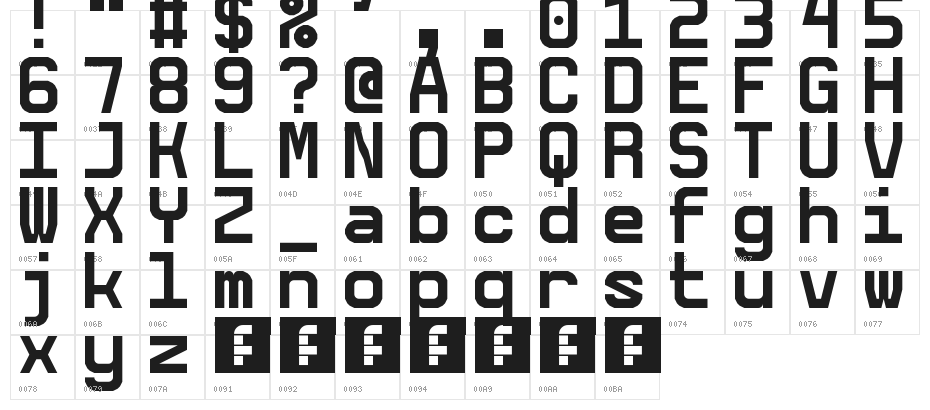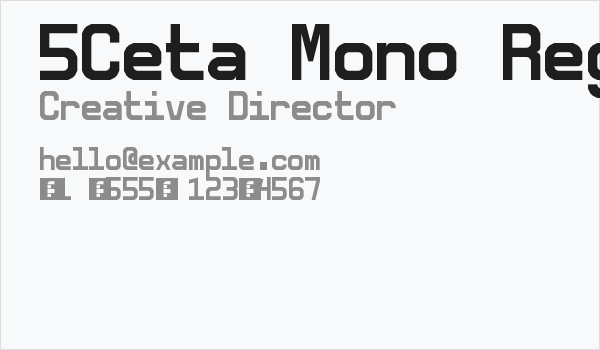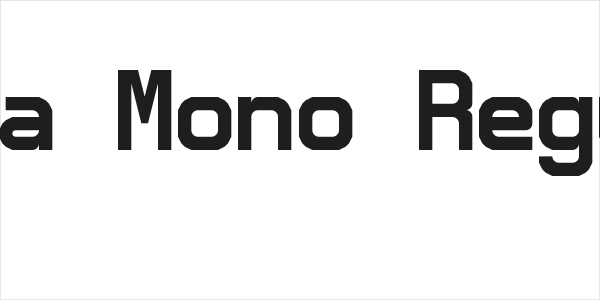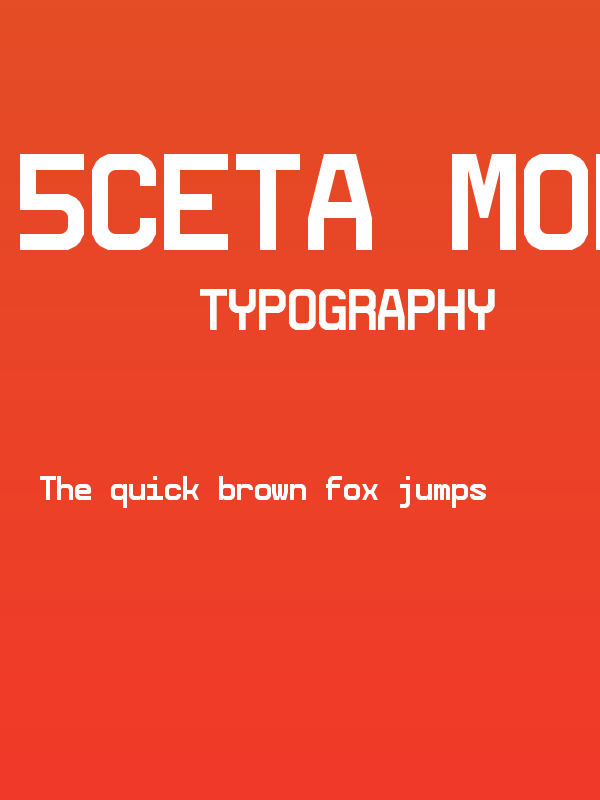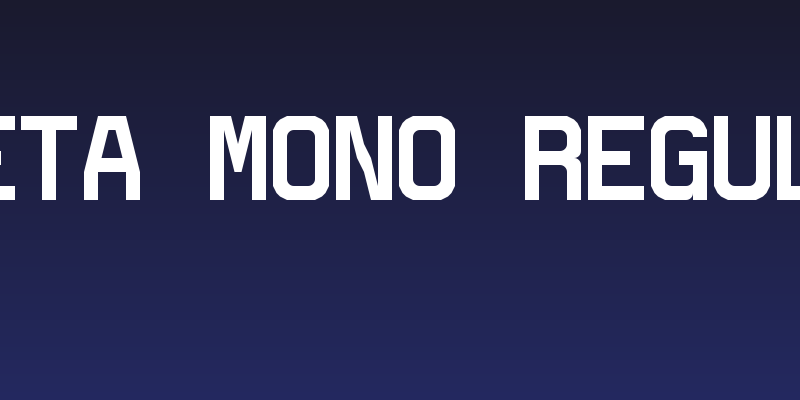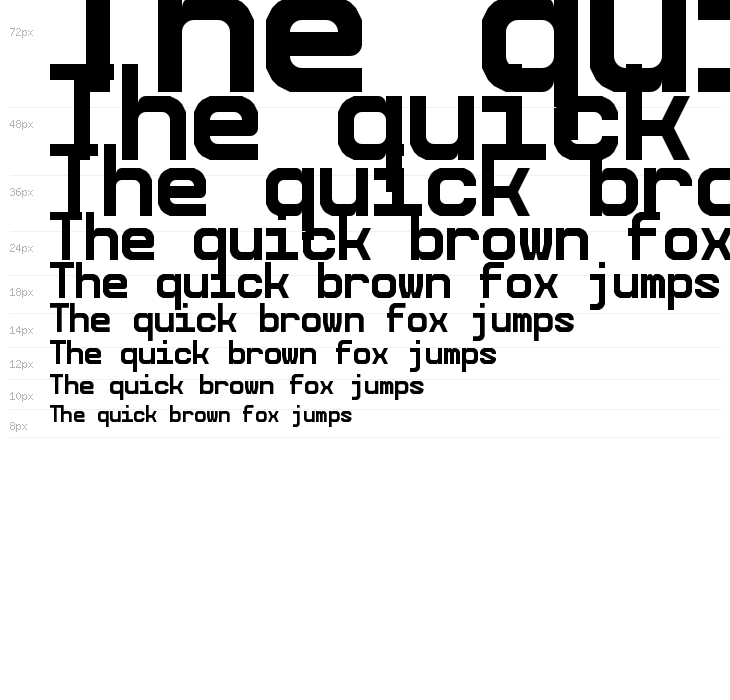
5Ceta Mono Regular Font
| Caso d'uso | Coding, Technical documentation, User interfaces |
| Progetti proposti | Ideal for coding environments, technical documentation, and any project requiring a clean, uniform typeface. |